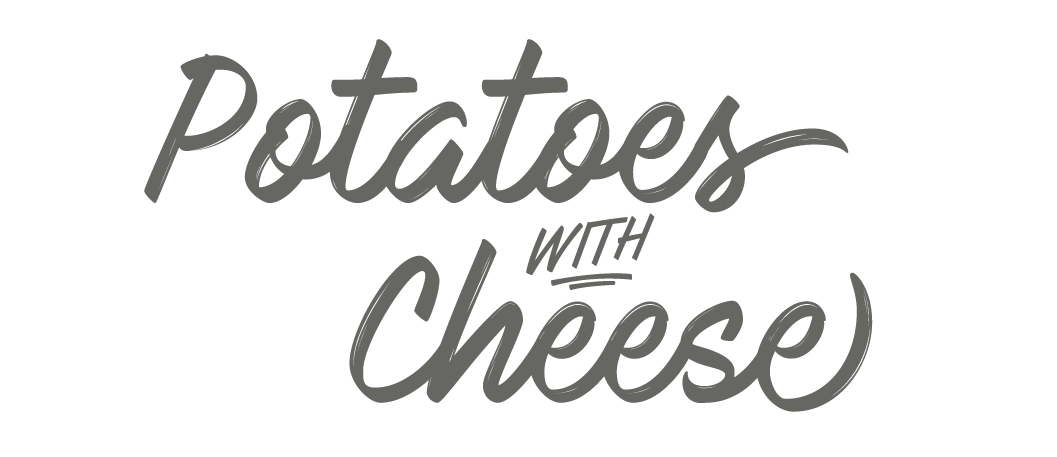
Определяет начертание шрифта — обычное, курсивное или наклонное. Когда
для текста установлено курсивное или наклонное начертание, браузер обращается
к системе для поиска подходящего шрифта. Если заданный шрифт не найден, браузер
использует специальный алгоритм для имитации нужного вида текста. Результат
и качество при этом могут получиться неудовлетворительными, особенно при печати
документа.
20 новых бесплатных рукописных шрифтов – Сей-Хай
Да-да, мы все любим такие истории. Одна компания выбрала правильный шрифт – и продажи выросли в 3 раза. А другая выбрала Papyrus – и ей везде мерещился Райан Гослинг (в принципе, неплохо).
Если вы рассматриваете свой бренд как открытый и позитивный, вам наверняка могут подойти рукописные шрифты. Такой вид типографики становится все популярнее.
От логотипов до графики в социальных сетях – они могут сделать ваш проект уникальным.
Мы собрали 20 крутых рукописных шрифтов, за которые вам не придется платить!
Из-за неровностей и грубых форм этот шрифт выглядит очень личным. Он идеально подходит для свадебных приглашений, рекламных плакатов, логотипов и поздравительных открыток.
Этот шрифт – неформальный и слегка запутанный. Его лучше всего использовать не как основной, а дополнительный. Он станет отличным акцентом, которым можно выделить несколько слов.
По словам создателя, Паулы Пейнмар, «этот шрифт был создан из почерка дизайнера в состоянии стресса». Он выразителен и смел.
Иногда рукописные шрифты могут выглядеть немного неровно. Однако шрифт Fofer понятен и легко читается, при этом оставляя чувство индивидуальности.
Этот рукописный шрифт доступен в двух стилях: жирный для объема и светлый для более тонкого, естественного стиля.
Этот бесплатный набор от Джереми Весси несет в себе современную эстетику каллиграфии.
Подобные шрифты часто используют в свадебных приглашениях, рекламе и социальных сетях.
Ищете веселый, неформальный шрифт? Rainy Day – идеальный вариант. Выглядит скромно и дружелюбно.
Этот экранный шрифт выглядит просто и обычно. Но при создает впечатление уникальности. Необычное сочетание, но нам нравится.
Этот шрифт основан на манере письма маркера Sharpie. Толстые, чистые линии делают его идеальным в случае, если вы хотите привлечь внимание к важному контенту.
Этот шрифт выглядит как каракули, зато позволяет вычеркивать или полностью заштриховывать буквы.
Дизайнер Сьюн Матрас поставила перед собой задачу создать шрифт, основанный на почерке отца. Он выглядит «очень личным и отлично подойдет для коротких сообщений и заголовков».
Название говорит само за себя: этот шрифт действительно выглядит «тощим». Буквы посажены очень близко друг к другу, и к тому же имеют неправильную форму.
Сложный и витиеватый шрифт выглядит как дорогая каллиграфия.
Olivia отлично подойдет для брендинга, лого или поздравительных открыток.
Naira – простой минималистичный шрифт. Крутой бонус: он идет с бесплатным пакетом акварельных паттернов (40 рисунков).
Грубые мазки создают ощущение суровости. Он написан заглавными буквами, что делает его хорошим вариантом для плакатов и подобных дизайнов.
Best Cursive Fonts — Cervanttis FontPIN IT
Cervanttis — лучший выбор для тех, кто ищет довольно характерный рукописный шрифт.
Cervanttis на самом деле представляет собой набор шрифтов в стиле подписи, которые можно использовать бесплатно, но для коммерческого использования есть ценник в 11 долларов.Тем не менее, шрифт стоит вложенных средств. Шрифты придают рукописный вид в фирменном стиле, что делает его идеальным для роскошных проектов и логотипов. При использовании на довольно мрачном фоне шрифт способен очаровать любой глаз.